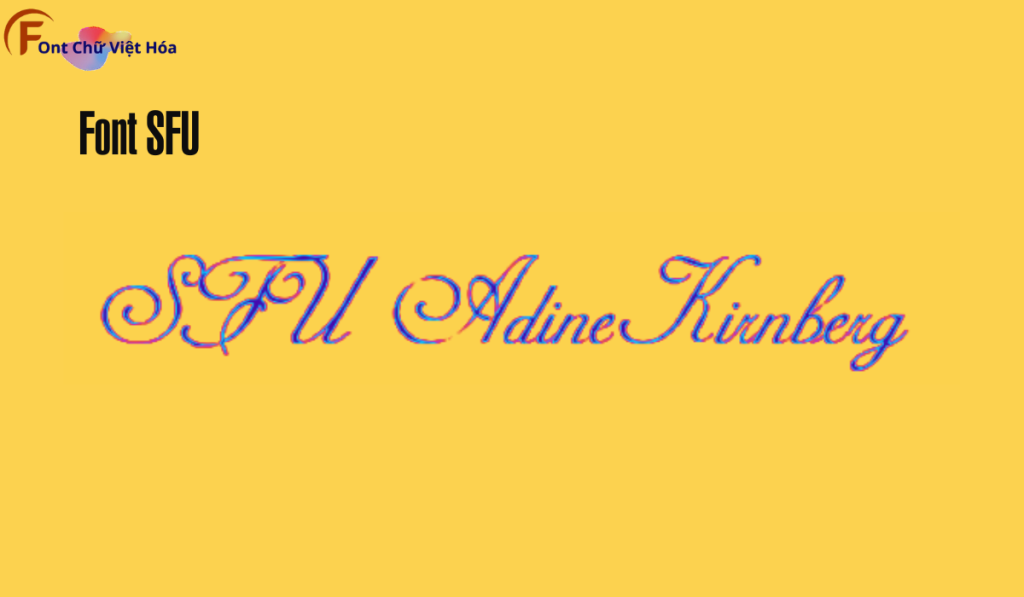
Font SFU Adinekirnberg Việt Hóa
Tác giả: Adinekirnberg
Bộ Font: SFU
Kiểu chữ: Chữ thảo
Font SFU Adinekirnberg Việt Hóa, thuộc bộ font SFU, mang phong cách chữ thảo với các đường nét mềm mại và tinh tế. Font này được thiết kế nhằm mục tiêu tạo ra sự thanh lịch và dễ đọc, đặc biệt phù hợp cho các thiết kế như thiệp mời, poster, và logo. Đặc điểm hình dạng của SFU Adinekirnberg là các đường nét rõ ràng và tỷ lệ chữ cân đối, giúp tạo ấn tượng thị giác mạnh mẽ và sự thanh lịch trong từng chi tiết. Font này cũng đã được Việt hóa, mang đến sự linh hoạt và tiện dụng cho các dự án thiết kế bằng tiếng Việt, giúp người dùng dễ dàng tiếp cận và sử dụng.